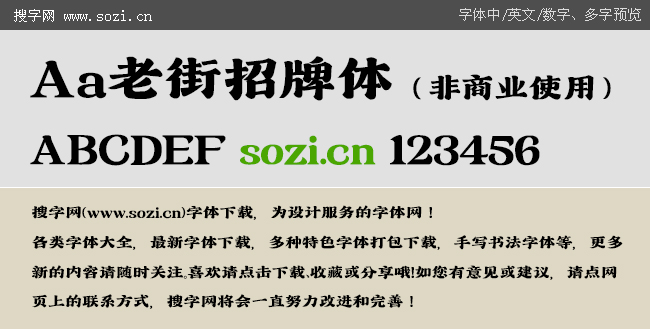
Aa老街招牌體
搜字網(wǎng)給大家提供一款A(yù)a老街招牌體(非商業(yè)使用)中文字體下載,Aa老街招牌體是一款手寫風(fēng)格的書法字體,該字體筆畫隨性且厚重飽滿,整體字形偏扁,融入了楷書的書寫韻味,結(jié)構(gòu)肆意灑脫,給人一種寬闊大氣飽滿流暢的感覺。適合應(yīng)用于海報(bào)設(shè)計(jì)、包裝設(shè)計(jì)、網(wǎng)頁設(shè)計(jì)等應(yīng)用(此字體為個(gè)人非商用版,商用可以聯(lián)系QQ:1006760504)。